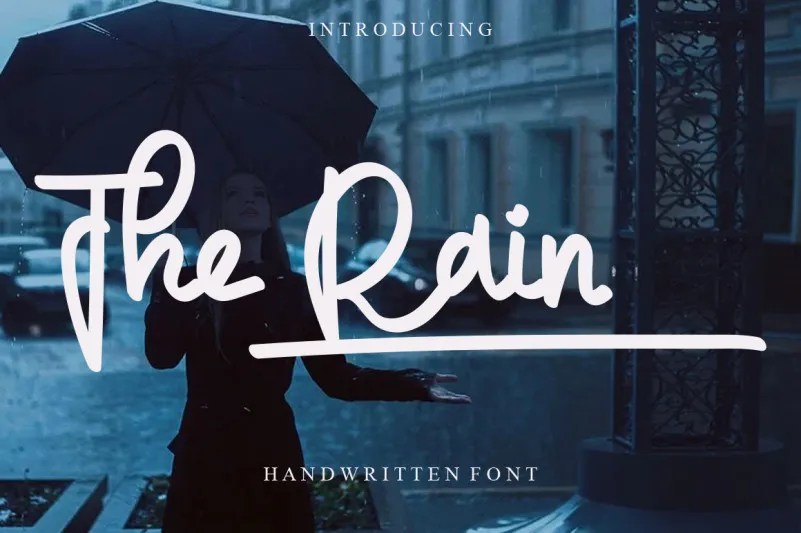
The Rain Font – Download Grátis
A The Rain Font é uma opção incrível para quem busca uma personalidade única que transmite alegria e amabilidade. Seja você artista digital ou aficionado por letra feita às mãos, essa fonte original pode transformar suas ideias criativas em verdadeiros obras de arte. Perfeita tanto para uso no Instagram quanto para desenhar letras a mão em projetos DIY, a The Rain Font oferece o estilo único e espontâneo que torna cada palavra ou frase uma peça única de arte. Composta por linhas leves e graciosas, essa fonte é perfeita para quem quer dar um toque especial às suas criações sem comprometer sua autenticidade. Perfect para qualquer projeto onde você precisa de uma escrita cuidadosamente elaborada que transmite empatia e alegria. Sem dúvida, The Rain Font é aquele que se destaca.